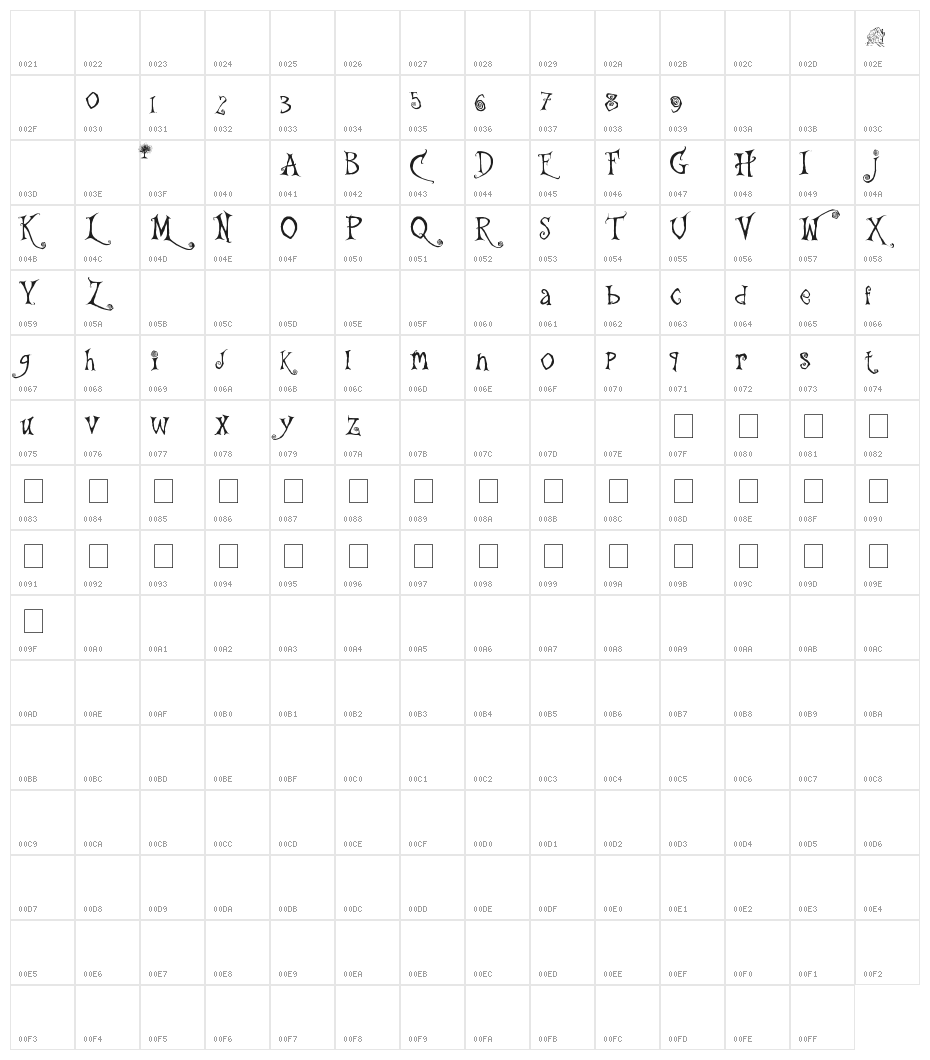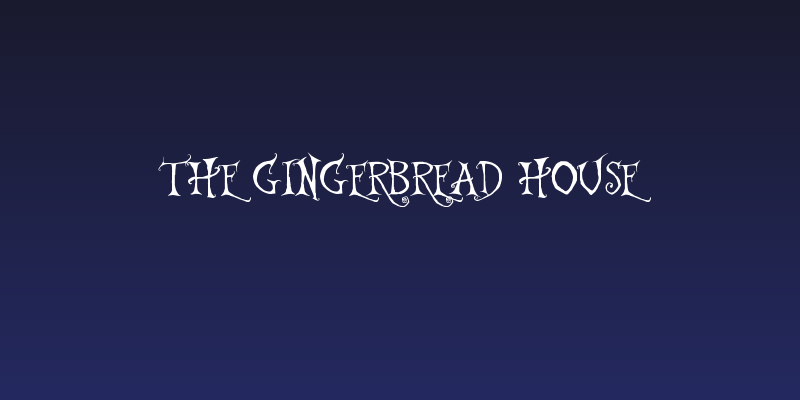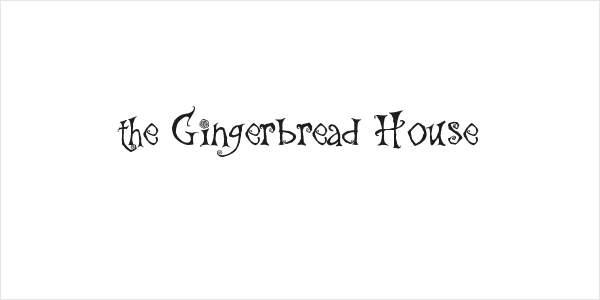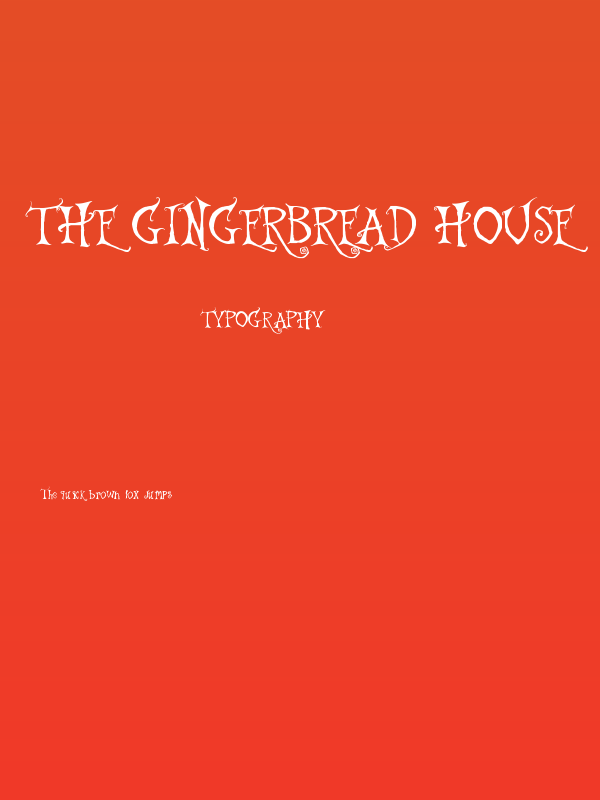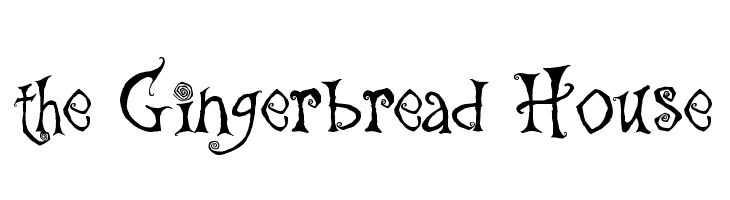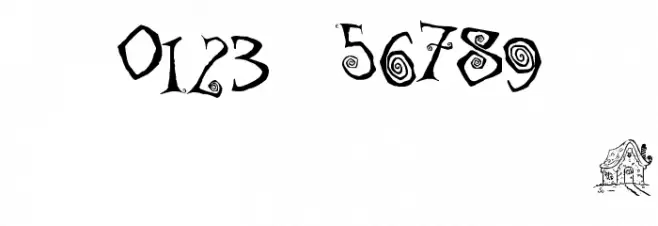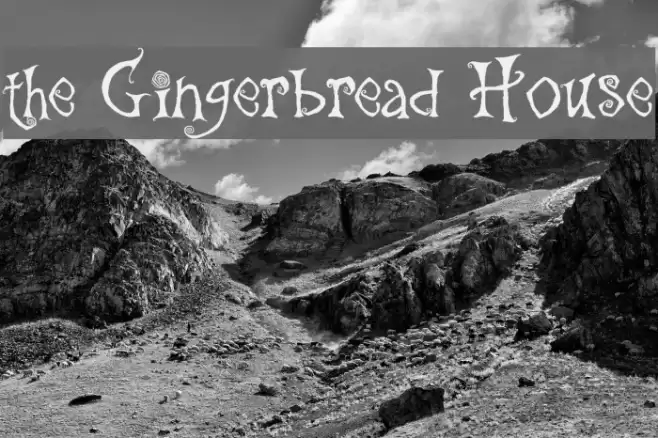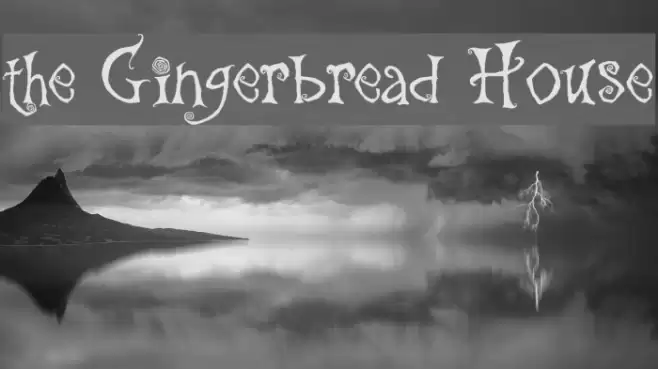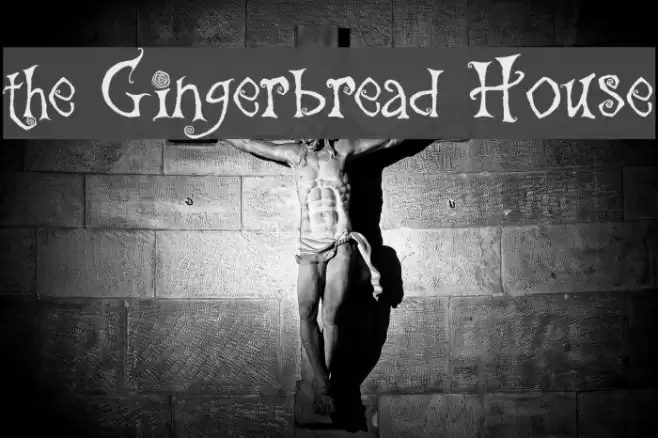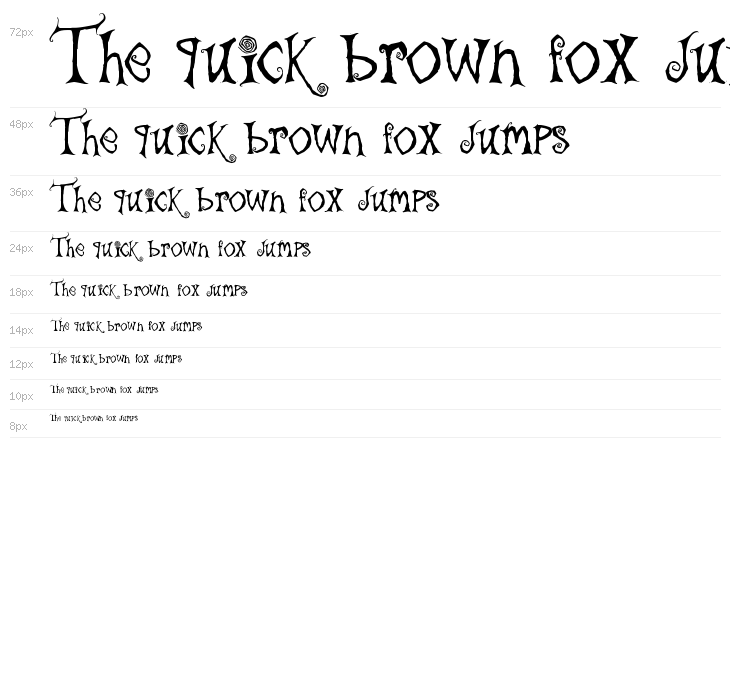
the Gingerbread House Font
Fonts by Christopher Hansen
| Nom | the Gingerbread House |
| Catégories | Round |
| Projets proposés | Ideal for children's books, fantasy-themed invitations, holiday cards, and playful branding. |
the Gingerbread House
| Auteur | Fonts by Christopher Hansen |
| Catégories | Round |